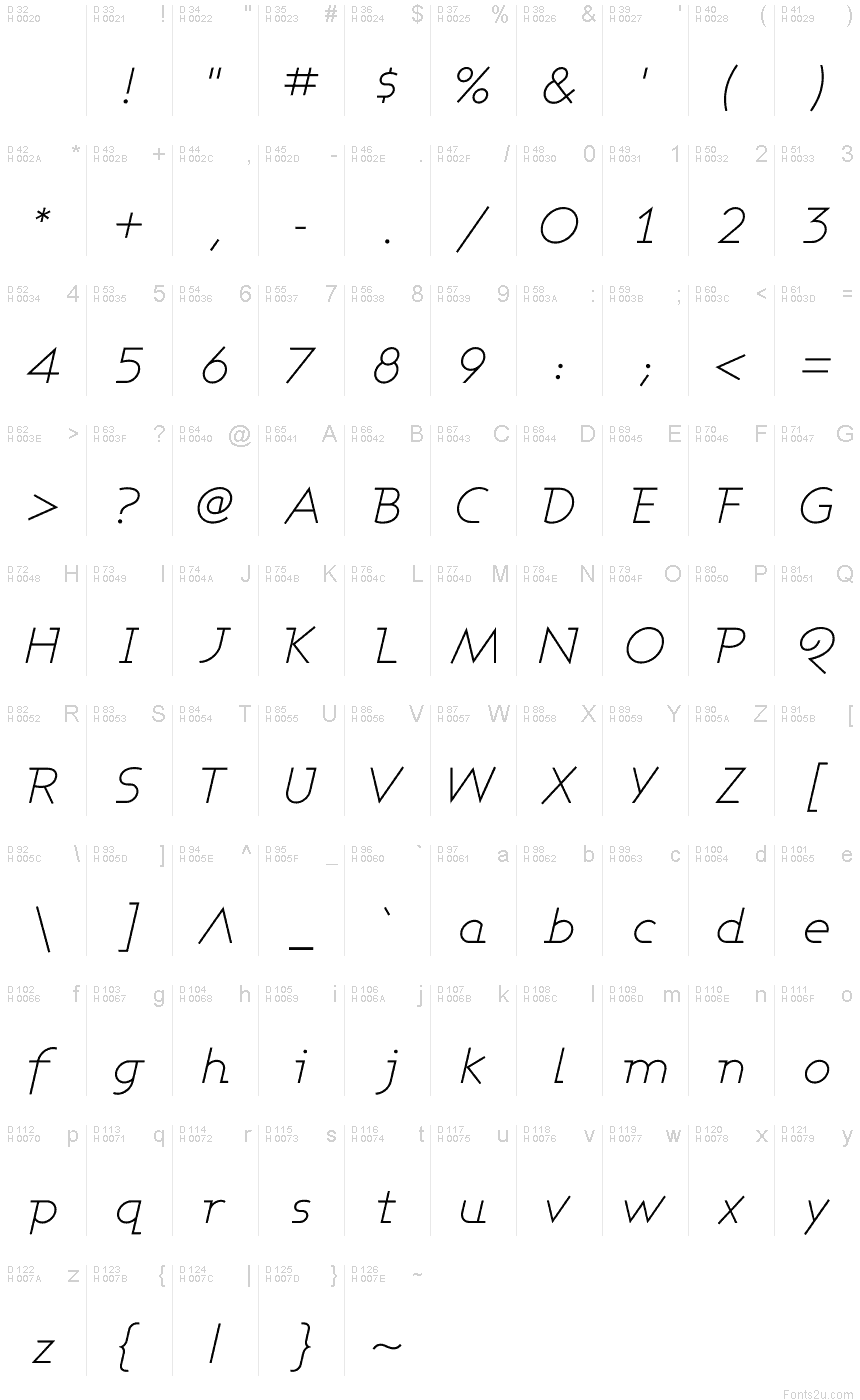
Ashby Light Italic
Ashby Light Italic autorstwa Robby'ego Woodarda to darmowy, lekki font bezszeryfowy, będący częścią rodziny Ashby Light. Jego wydłużone, lekkie pochylenie nadaje projektom dynamiki bez przesadnego ozdobnika, jaki niosą fonty skryptowe, a wyjątkowo cienkie kreski sprawiają, że całość jest wyrazista, nowoczesna i utrzymana w modowym stylu.
Ashby Light Italic świetnie sprawdza się w nagłówkach magazynów, identyfikacji wizualnej butików, opakowaniach perfum i kosmetyków, grafikach z cytatami, minimalistycznych plakatach, okładkach albumów oraz w głównych hasłach na stronach www. Użyj dużego stopnia pisma, aby pozwolić wybrzmieć jego eleganckiemu pochyleniu, i zestaw ten darmowy font z solidnym, neutralnym krojem bezszeryfowym w tekście głównym lub mniejszych detalach.